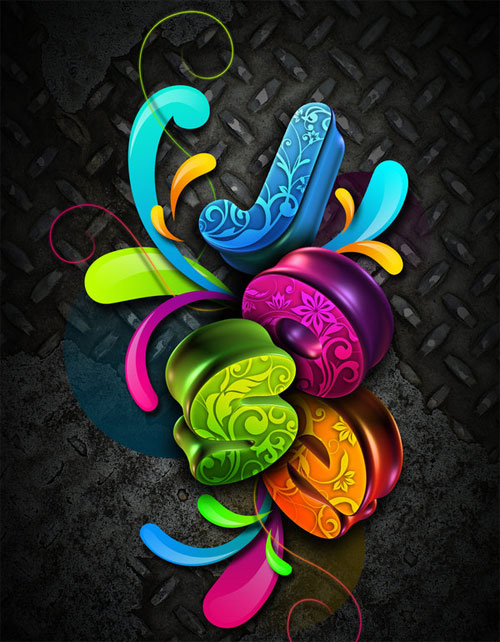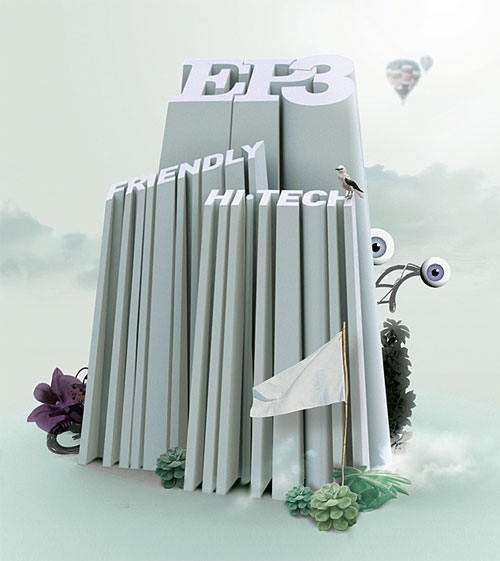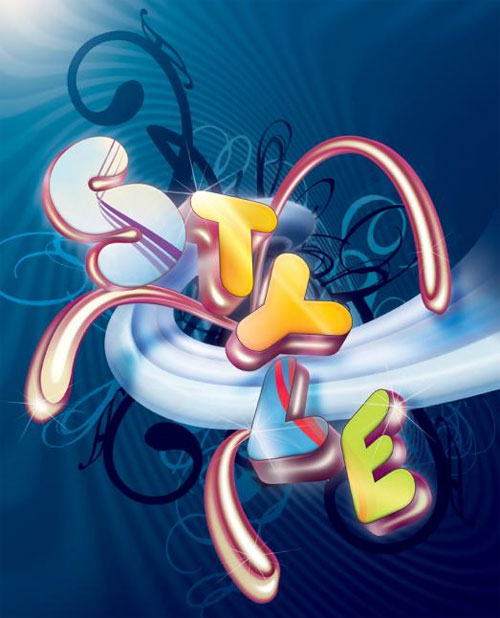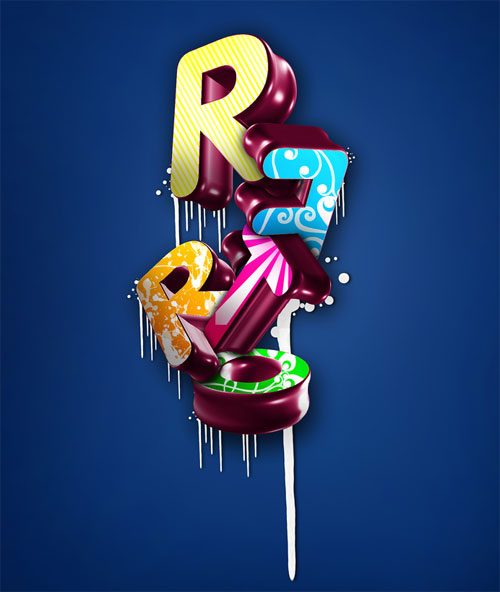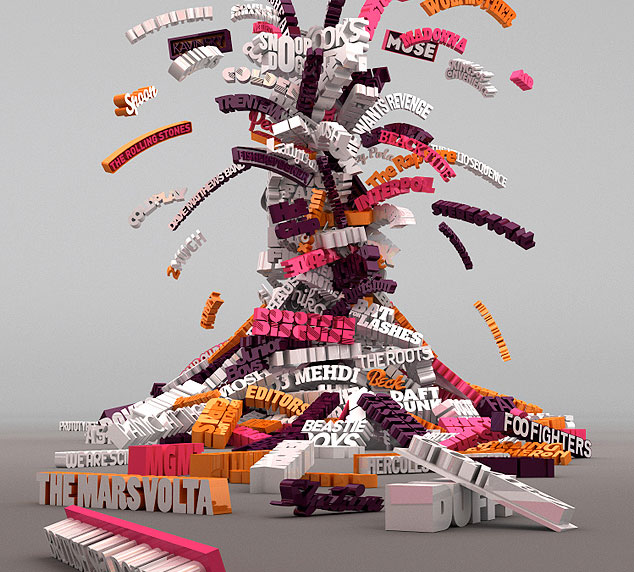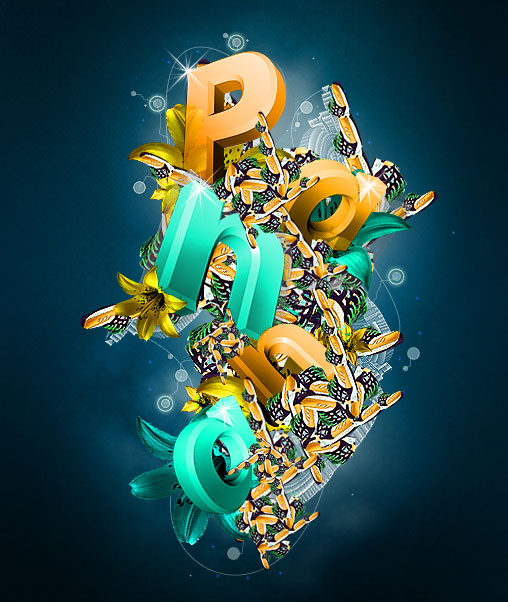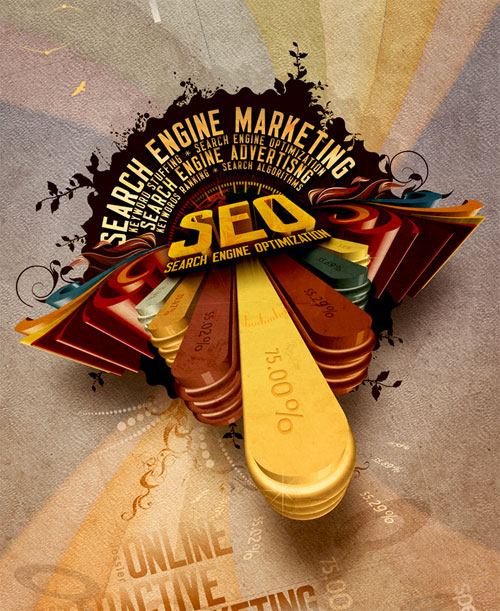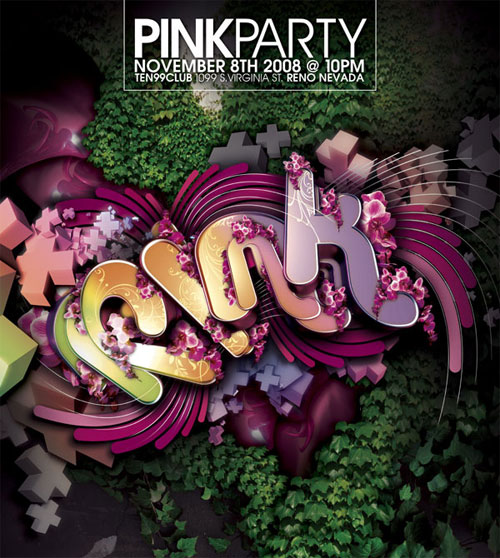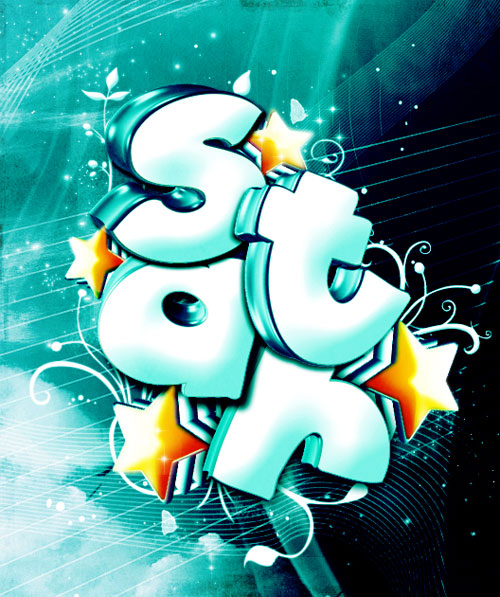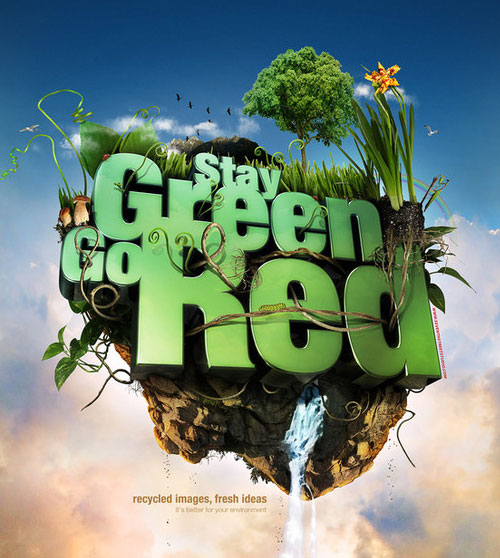
Inspiração Tipografia 3D
Uma das tendências em alta na criação são os projetos de tipografia. Esses projetos são normalmente são criados em 3D para dar efeitos de profundidade e brilhos incríveis. Alguns designers são ainda a introdução de tipografia 3D particularmente em projetos web, ou até mesmo para os comerciais. Na maioria dos casos o designer usa alguma ferramenta de modelagem 3d como 3D studio max ou até mesmo pela ferramenta de 3D do illustrator. Se você gostar do post e quer aprender um pouco mais sobre tipografia em 3D, confira uma lista no post Tutorial Tipografia no Illustrator ou até mesmo inspire-se mais com o post Exemplos de Tipografia 3D que postamos no começo do nosso blog.